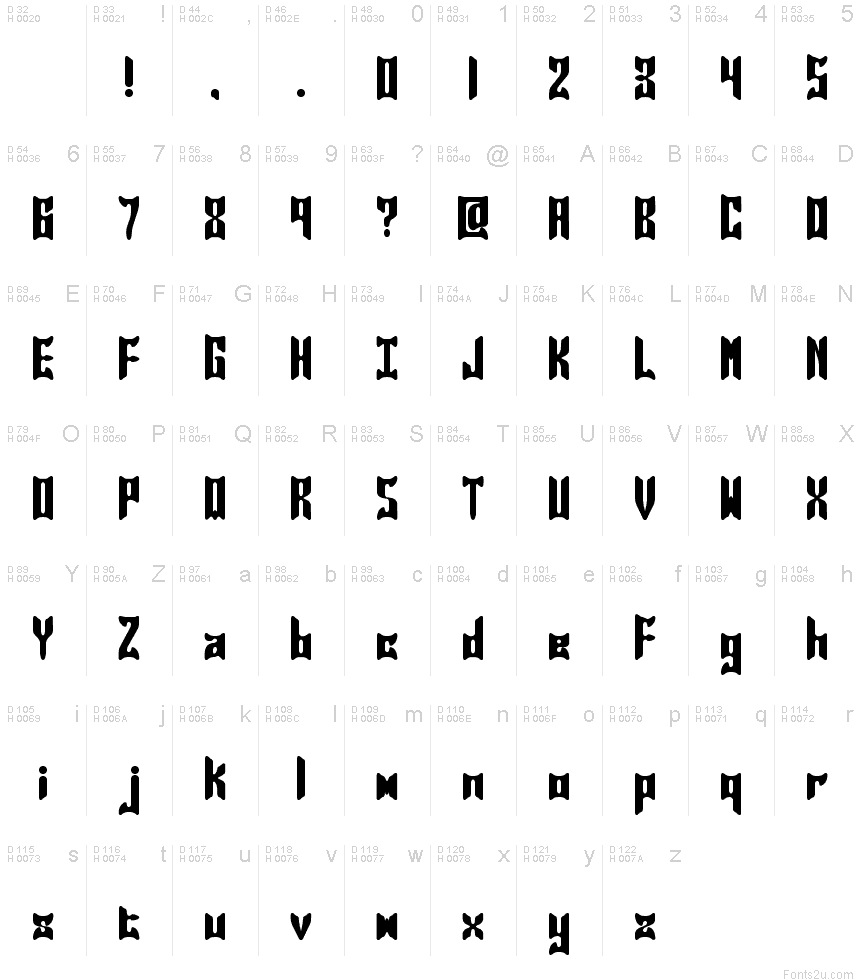
Jasper Solid di Ænigma Fonts è un font gotico display gratuito con una texture meravigliosamente inchiostrata e gocciolante, che trasmette l'idea di un rituale misto a un poster rock. I tratti alti e affusolati e le giunture irregolari creano un aspetto denso, quasi scolpito, come se le lettere fossero state tagliate nella pietra nera e lasciate sciogliere sui bordi. Il ritmo è serrato e continuo, facendo sì che le parole sembrino sigilli audaci piuttosto che singoli caratteri, rendendo ogni parola o breve frase di grande impatto.
Con Jasper Solid, l'atmosfera diventa protagonista. Questo font gratuito brilla su loghi di band, copertine di album metal o doom, titoli horror, zine occulte, volantini di feste underground, schermate di giochi e merchandising audace. Usalo in grande formato e lascialo respirare; funziona al meglio in linee brevi e incisive. Per il testo di accompagnamento, abbina Jasper Solid a un font sans serif pulito e neutro, lasciando che queste forme pesanti e scolpite rubino la scena.